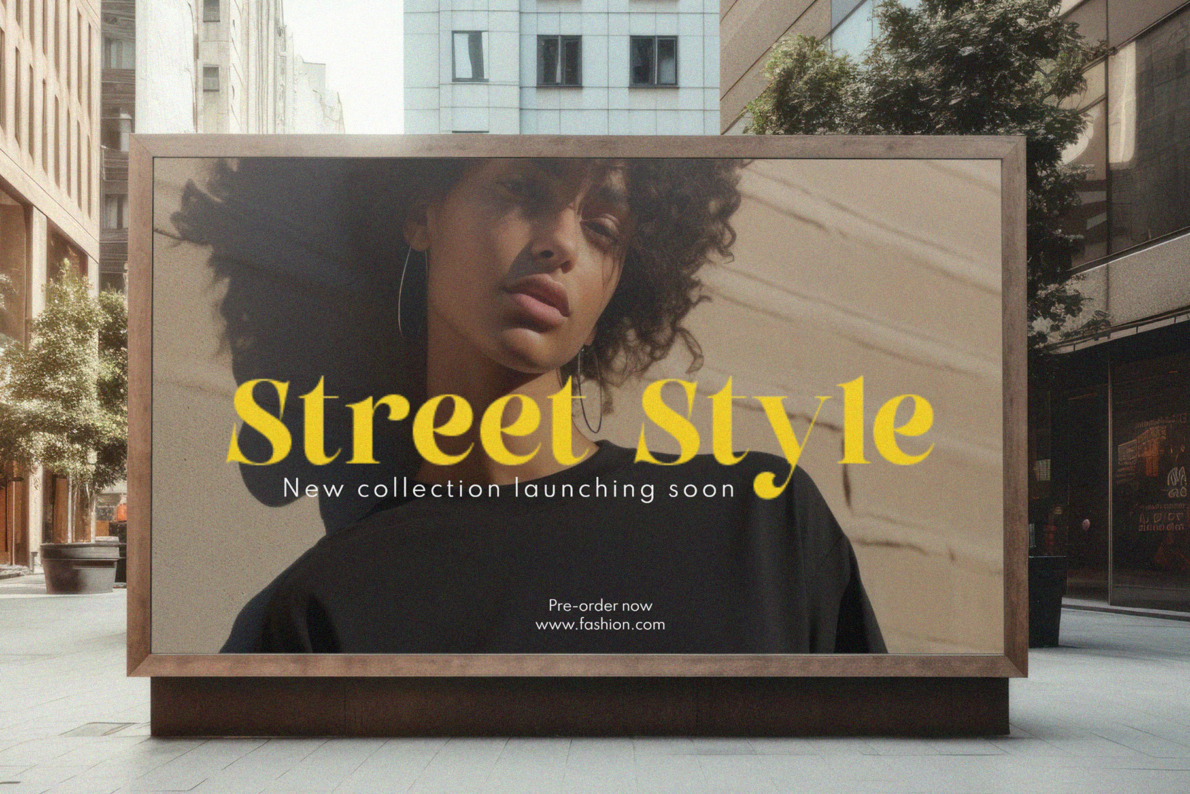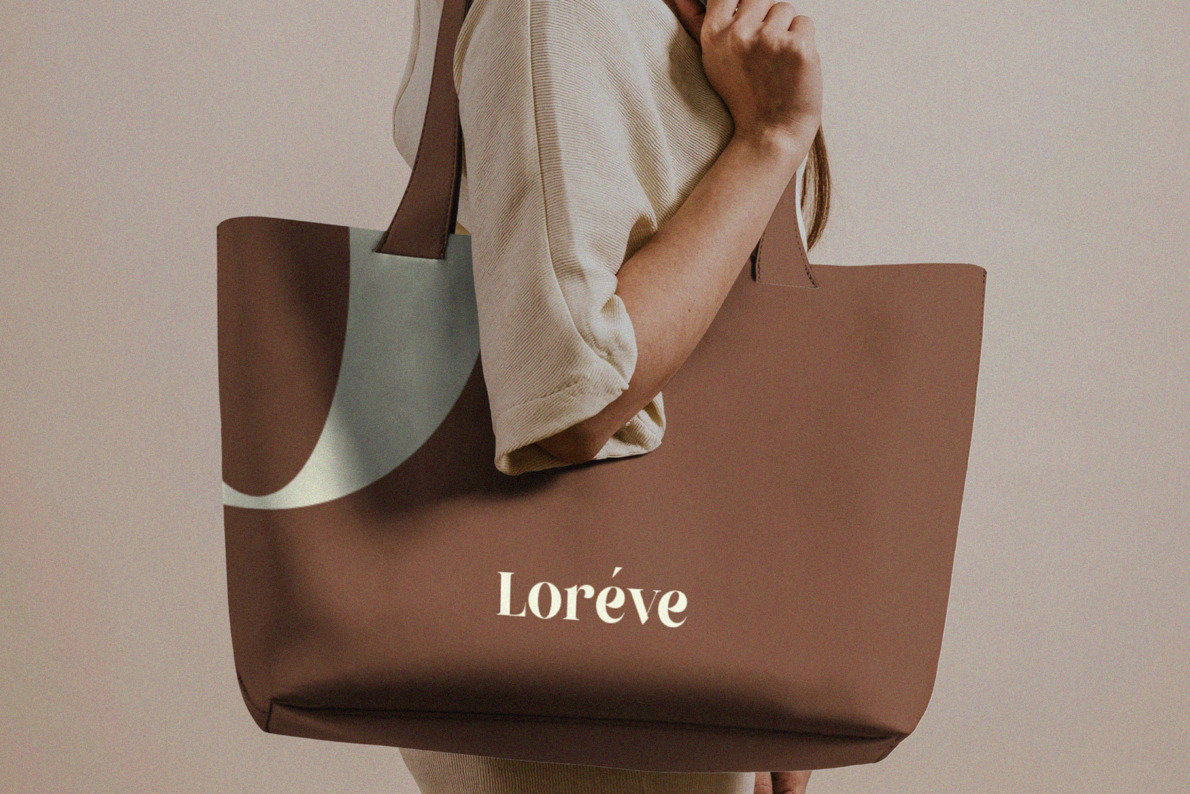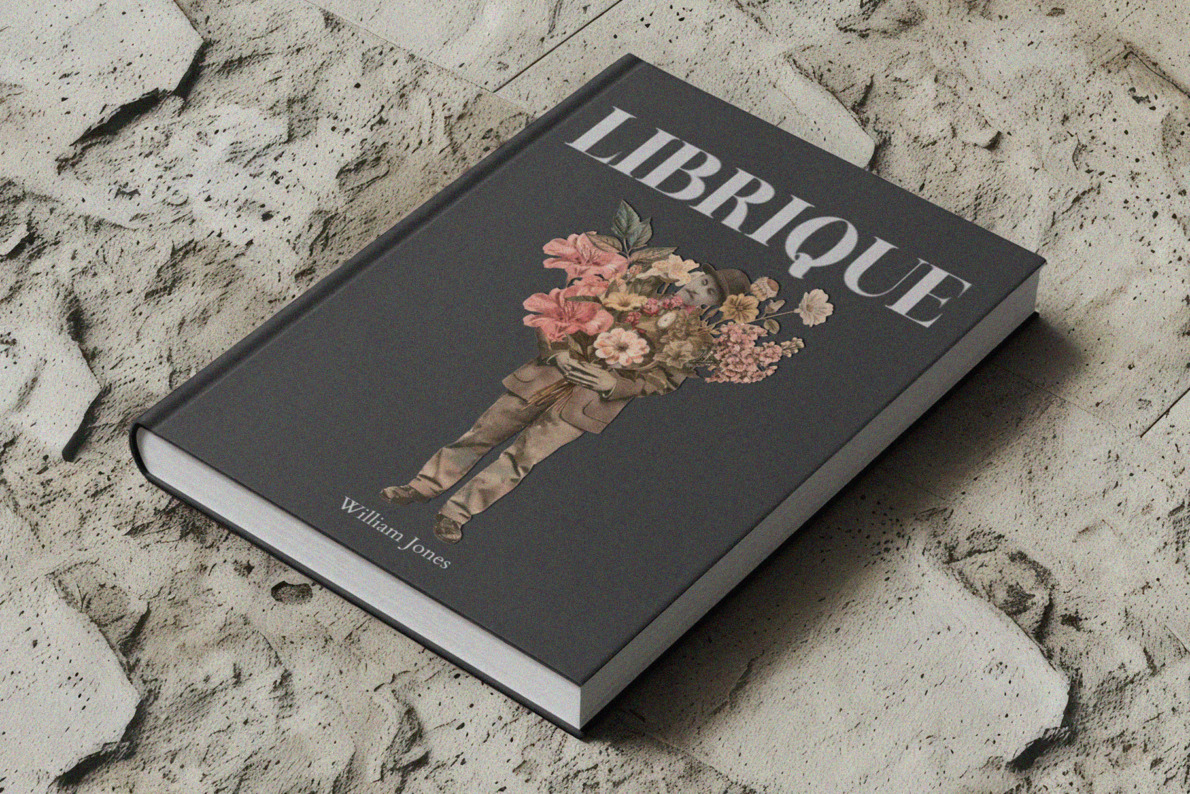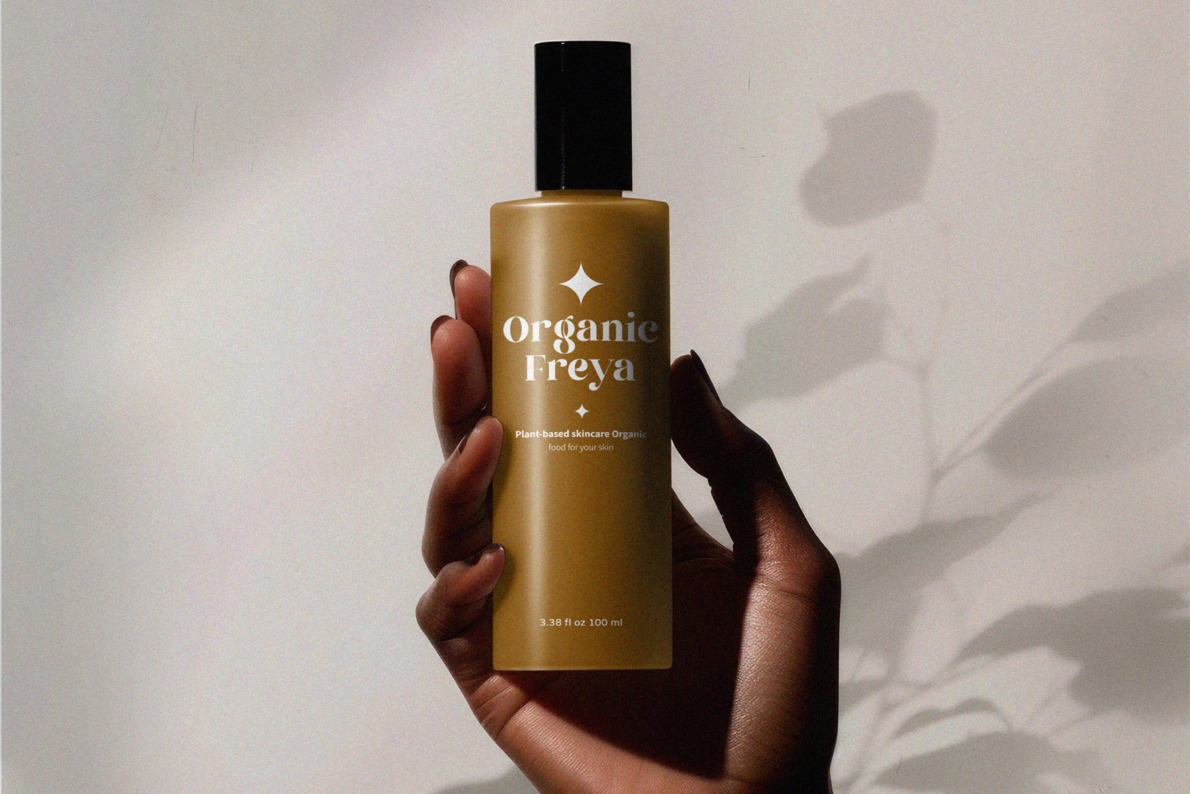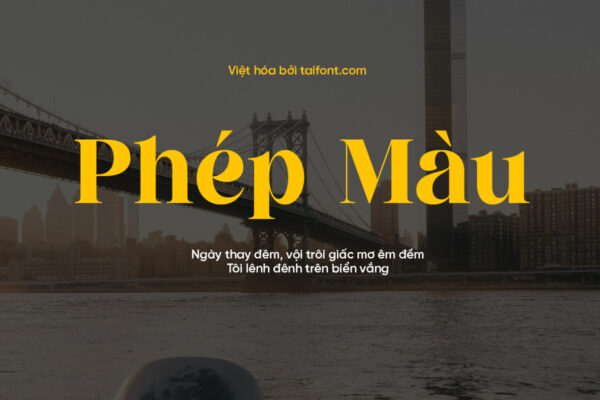
Giới thiệu về Font TF Andaluz Việt hóa
TF Andaluz Việt hóa là một font chữ có chân (serif) nổi bật với thiết kế nét đậm, đầy đặn và mang vẻ đẹp mạnh mẽ, sang trọng. Font này toát lên phong thái cổ điển pha lẫn hiện đại, với những đường nét được chăm chút tỉ mỉ, tạo cảm giác về sự vững chãi và tinh tế, lý tưởng để thu hút sự chú ý.
Với đặc điểm là nét đậm, tính thẩm mỹ cao và phong thái ấn tượng, Andaluz là lựa chọn hoàn hảo cho các thiết kế muốn truyền tải sự đẳng cấp và sự độc đáo, đặc biệt là trong các lĩnh vực:
- Thiết kế thời trang: Hoàn hảo cho các thương hiệu thời trang cao cấp, từ logo, nhãn mác sản phẩm, lookbook, đến các chiến dịch quảng bá bộ sưu tập. Font này giúp truyền tải vẻ đẹp thanh lịch, đẳng cấp và độc đáo của trang phục, nâng tầm giá trị thương hiệu.
- Thiết kế tiêu đề: Lý tưởng để tạo các tiêu đề chính trên poster, banner, hoặc các ấn phẩm truyền thông cần sự chú ý tối đa. Nét đậm và hình dáng nổi bật của Andaluz giúp thông điệp của bạn “nhảy” ra khỏi trang, dễ dàng gây ấn tượng sâu sắc.
- In ấn: Đảm bảo khả năng đọc tốt ngay cả ở kích thước lớn, và tạo hiệu ứng thị giác mạnh mẽ khi in trên các chất liệu khác nhau như giấy, vải, hay biển hiệu.
Với TF Andaluz Việt hóa, bạn có thể dễ dàng thổi hồn mạnh mẽ, năng lượng và sự độc đáo vào các thiết kế, tạo ra những sản phẩm không chỉ đẹp mắt mà còn cực kỳ ấn tượng và có khả năng thu hút sự chú ý tối đa.
Font Việt hóa TF Andaluz – Phong chữ thời trang